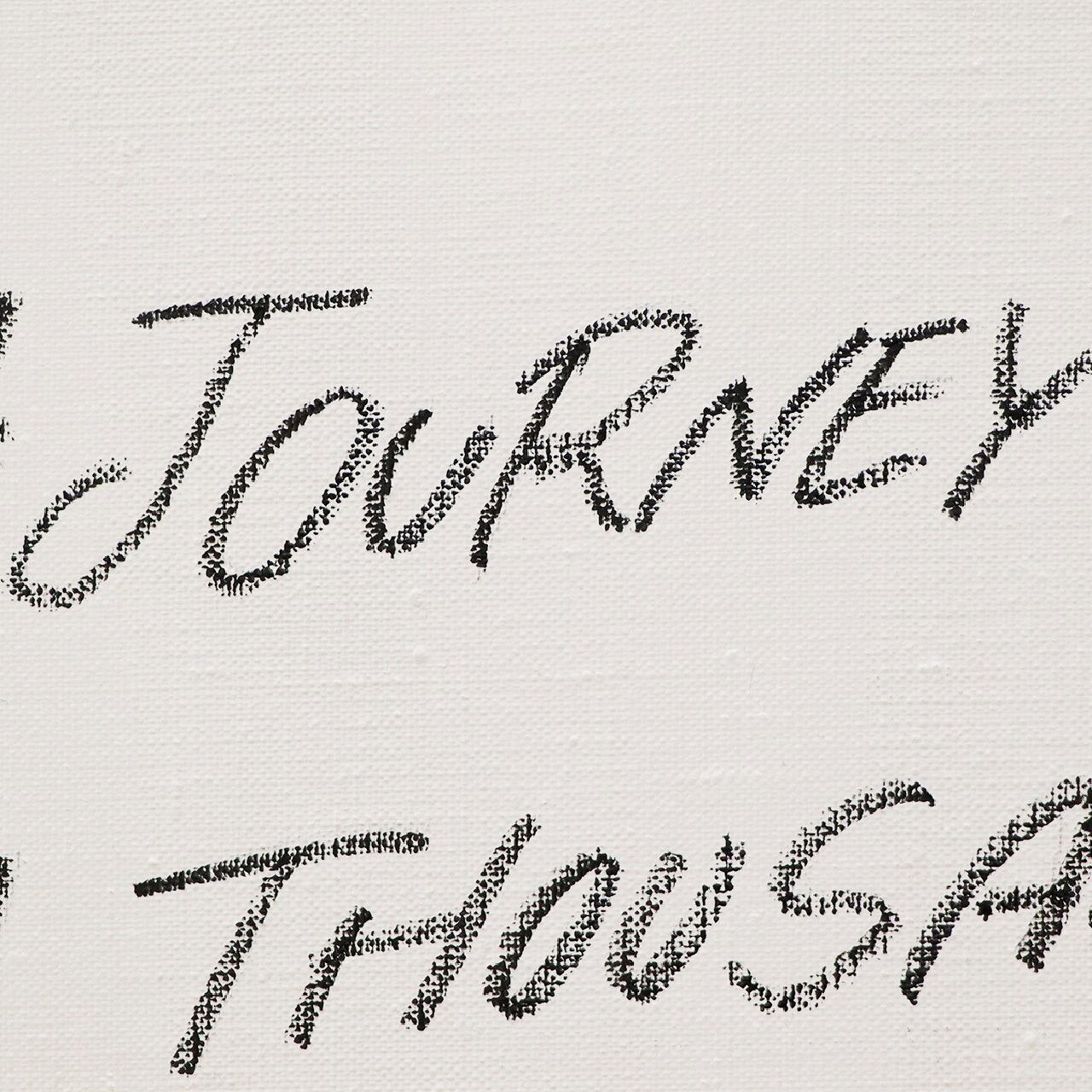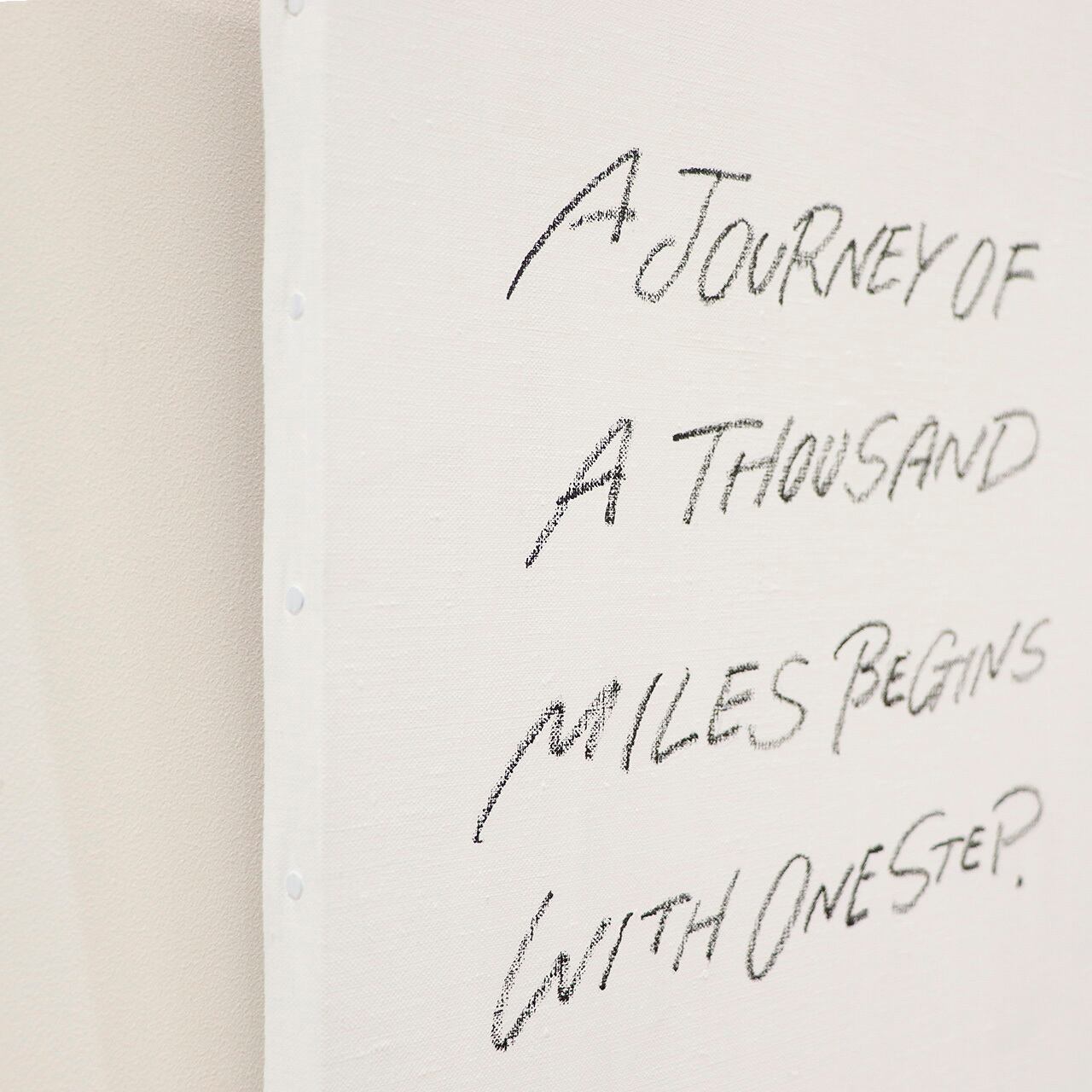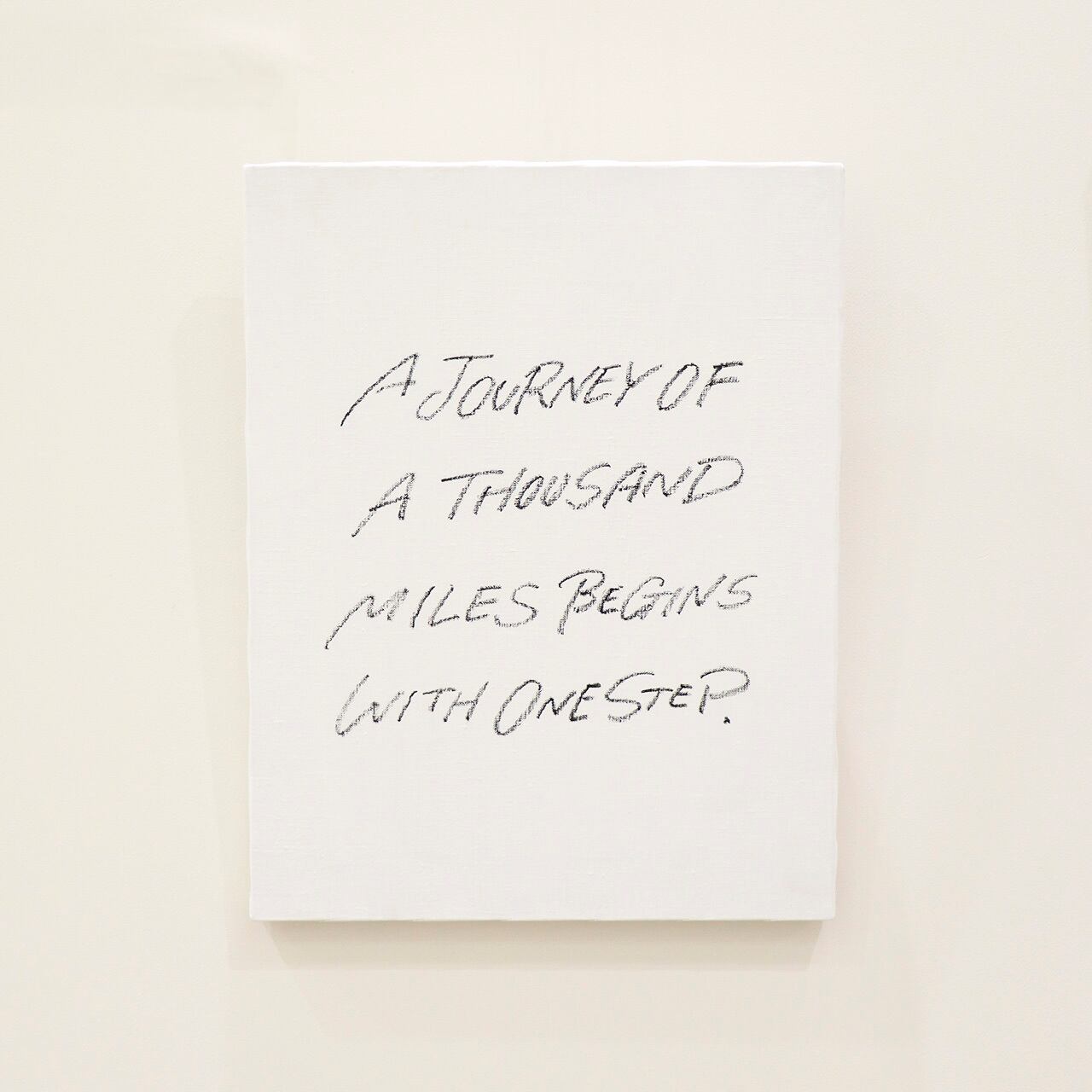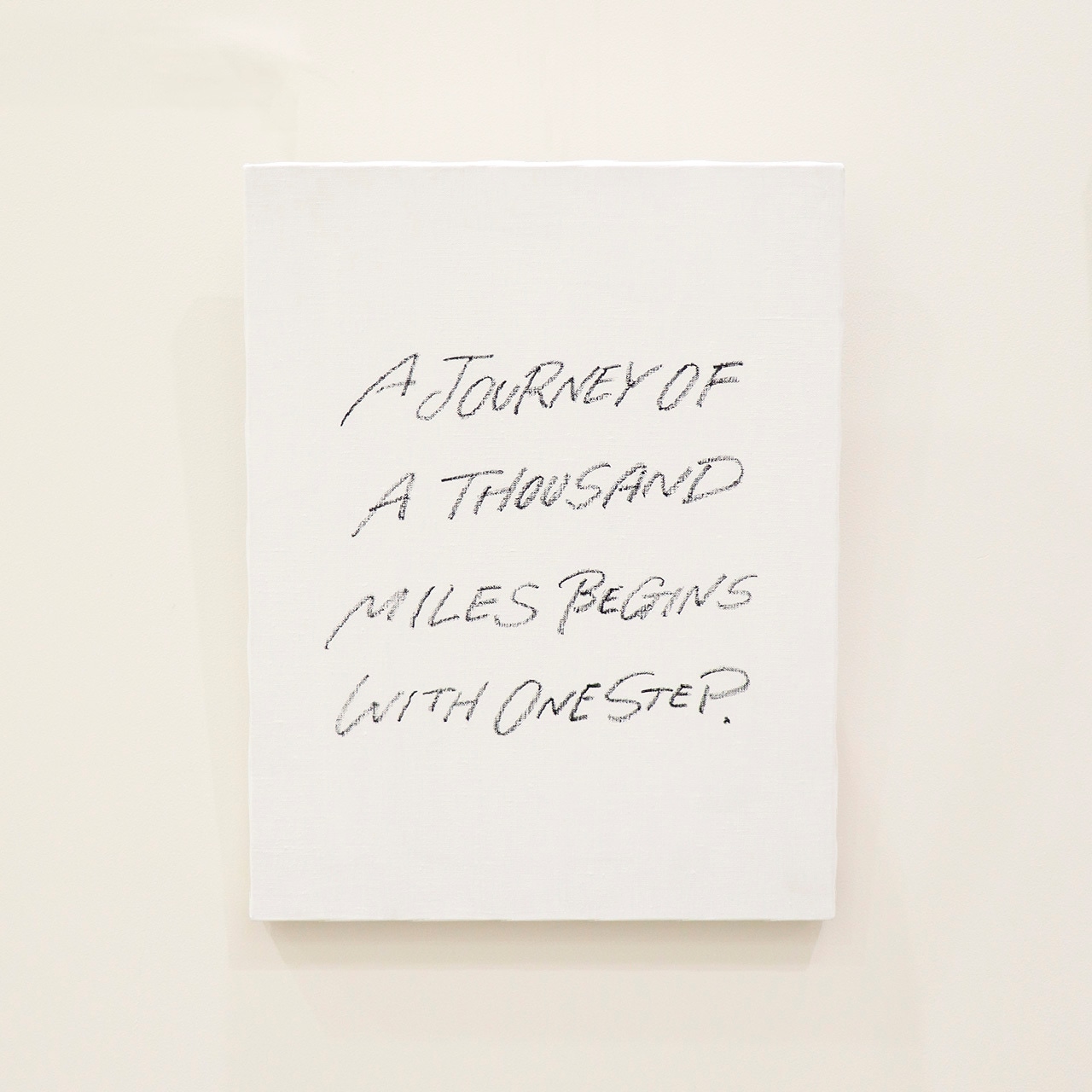
A JOURNEY OF A THOUSAND MILES BEGINS WITH ONE STEP.
千里の道も一歩から
長年文字を描くことを続けてきて、「原点に戻ろう」と思った時に出てきた言葉です。
最初は黒板で始まったので、色は違いますがチョークっぽいペンで描いています。
コツコツ続けることは難しいですが、踏ん張って続けたいことがある人に。
チョークやクレヨンのように見えますが、固形ペンキというもので描いているので落ちる心配はありません。